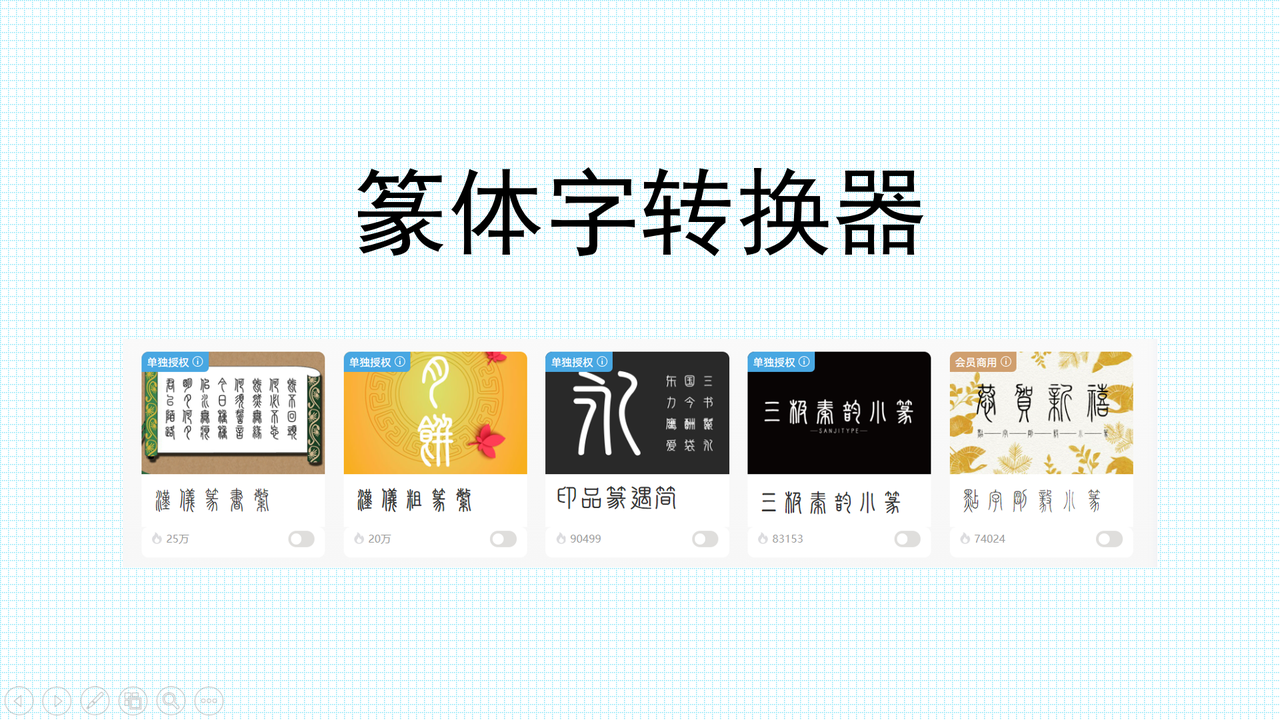
篆体字转换器哪个好?用字由就够了!
书法字体一直都是设计行业的潮流,因为它不仅保留了古代书法的文化底蕴,还能给作品增添一份庄重感和专业感。但传统的篆体字生成器问题太多了,比如打开之后经常弹出广告、生成的字体效果很差又不规范、有时候判断不了版权归属。今天就给大家介绍一款完全稳定的篆体字转换器——字由,它是国内领先的字体管理工具,拥有海量正版的字体资源,推出了多款高品质篆书字体,更是与汉仪字库、三级字库等头部字体厂商深度合作,字体版权完全可以得到有力保障。本文将从字由的优势、篆体字转换流程到热门篆体资源推荐三个方面详细来介绍,一起来看看吧!
一、为什么选字由?篆体字转换器的核心优势
大家都知道,市面上的篆体字转换器五花八门,随便一搜就能搜出一大堆,为什么要给家推荐字由?原因非常简单——字由可以解决设计师真正的痛点,不仅仅是实现篆体字转换这种单一的需求。它是面向设计师用户提供字体应用,管理,授权服务,并提供 AI 识字、字体特效等实用设计工具的全方位字体管理神器。
3.AI 字体功能一键生成篆书效果
字由除了优质的字体资源,还内置了 AI 字体功能,里面藏有大量艺术字模板。用户只需要选择自己心仪的模板,输入文字内容,就可以一键获得同款字体,下载为透明背景的 PNG 图片之后,直接拖进海报作品中就能用。
二、篆体字转换流程
1.输入文字一键转换当前效果
第一步:进入字由的字体资源页面
在搜索引擎搜索“字由”,选择官网进入,在首页顶部导航栏点击“全部字体”。
第二步:按风格筛选篆体字
用户可以直接在搜索框输入“篆”,下方页面就会弹出字由内的篆体字模板,点击选择一款自己想要的风格。
第三步:输入文字完成转换
在字体详情页面,在文本框内输出文字,就能转换为当前篆书字体的效果。
2.客户端实现在 PS、sketch 中的字体一键转换
第二步:搜索篆书字体。
用户注册登录字由客户端之后,在客户端的搜索框输入“篆书”,或者通过左侧筛选栏进行筛选,即可看到字由整理的专业篆书资源。
第三步:一键激活并完成字体转换
在 PS 等设计软件中选中需换字文本,回到字由客户端,找到心仪的篆书字体,点击右侧“激活”按钮,即可完成字体应用。后续你想怎么修改字体都可以在设计软件中进行了,这款字体就归你了!
三、热门篆体字资源推荐
1.汉仪篆书繁(单独授权)
汉仪篆书繁是汉仪字库推出的经典篆书字体,笔致遒劲,间隔均衡,追求偏长秀气和幽雅、古朴,是字由平台上最受欢迎的篆体字体之一。线条没有丝毫现代的锐利感,非常圆润稳重,自带一种深厚的历史底蕴。这款字体适合用于古籍封面、电子排版、古风海报、传统节庆礼盒包装等场景。
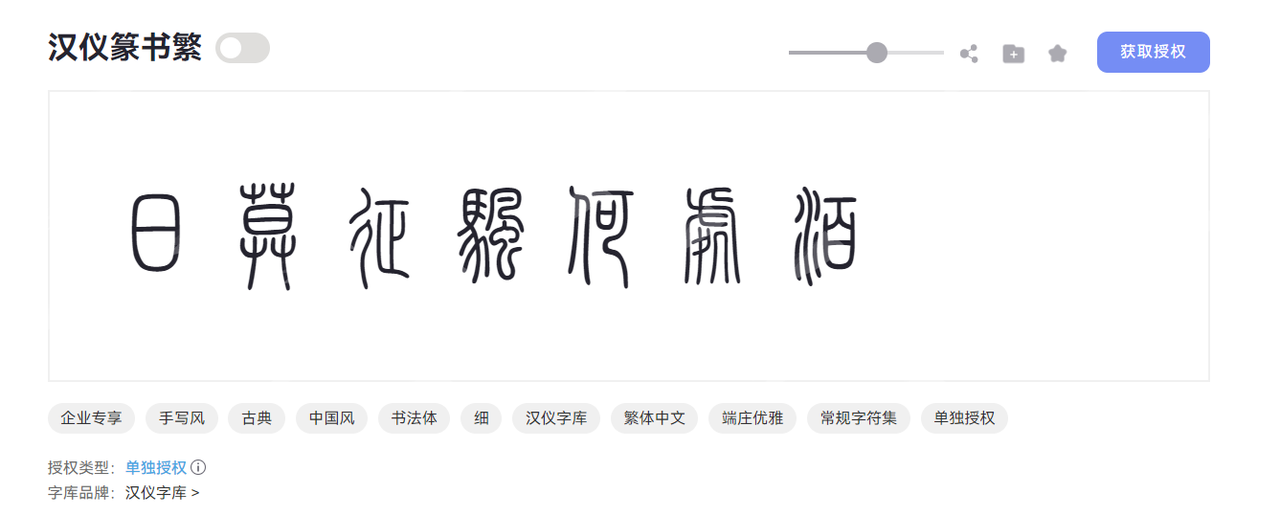
2. 三极秦韵小篆(单独授权)
三极秦韵小篆是三极字库出品的秦朝风格篆书字体,保留了秦朝时期篆书的特点,圆润均匀的线条、修长的字形、近似左右对称的结构。但是相比秦篆,它的笔画更有手写的温度感,线条变化比较贴近毛笔书写的真实质感,给人一种古典且温柔的美感。该字体适合用于文创设计、古风餐厅菜单、春联、文艺作品封面等文人气息较重的场景里。
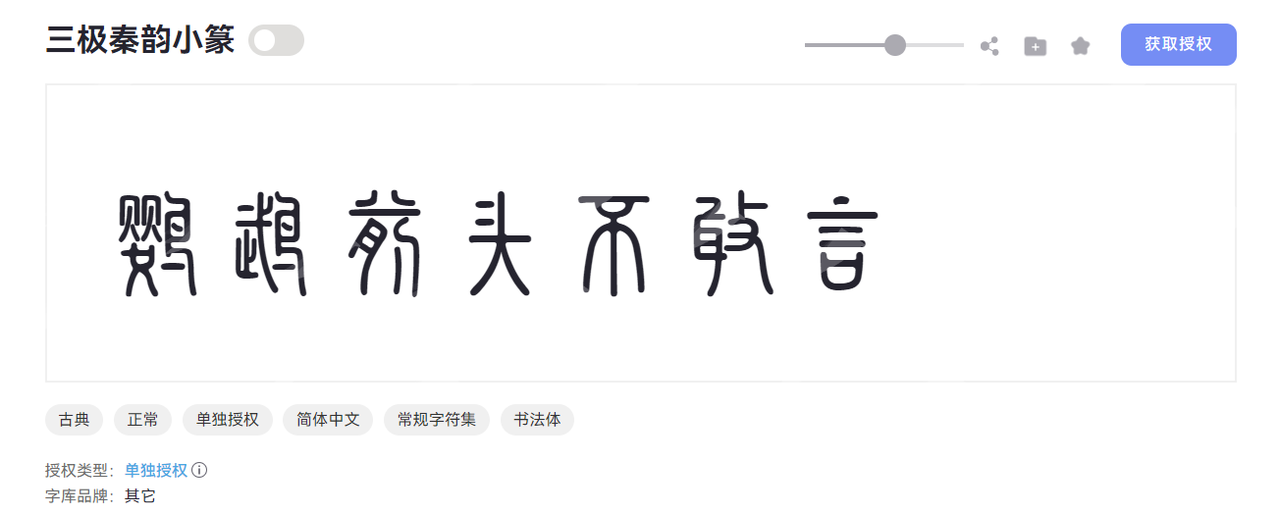
3.汉仪粗篆繁(单独授权)
汉仪粗篆是是由汉仪字库开发的一款现代艺术篆书字体,比汉仪原有的篆书笔画更粗一些,完美地融合了古典韵味与现代设计感。在古典小篆典雅匀称的结构基础上,进行了大胆的现代化、美术化处理,将笔画大幅加粗,形成强烈的块面感与视觉张力,同时保留了篆书特有的婉转流畅的笔意和装饰性。该字体适合用于国潮品牌 logo、武侠类书籍封面、游戏页面设计、音乐会海报等艺术气息浓烈的场景。
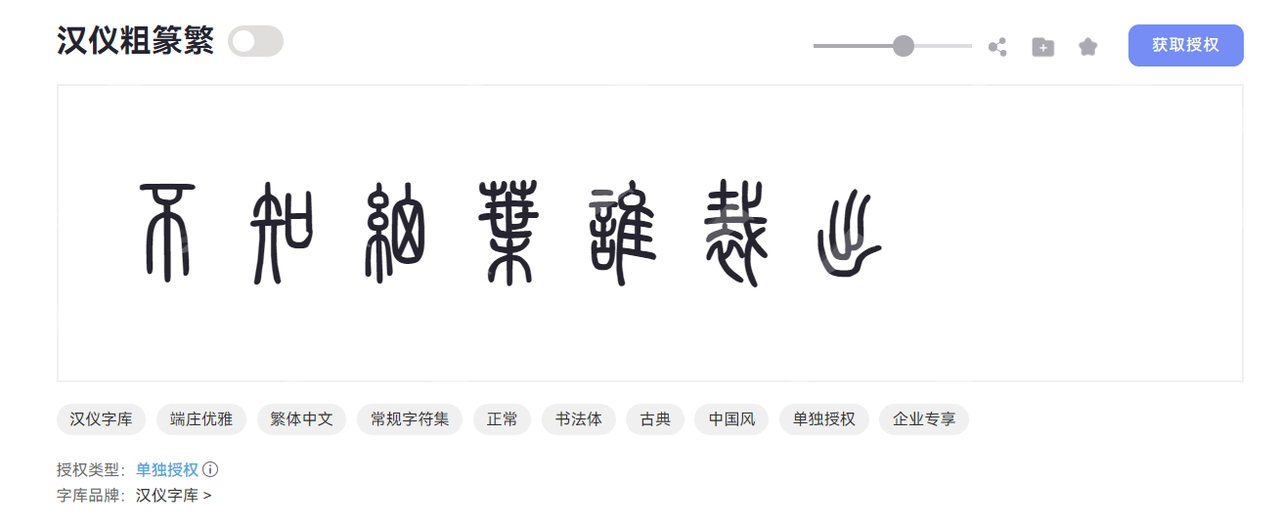
以上就是关于字由的详细介绍,用它来进行篆体字转换真的是再方便不过了!从多样化且实用的功能到全能的字体版权保障,再到丰富的篆体资源,更是优化了字体应用的流程,完全满足设计师在篆体设计中的所有需求。不管是古风文创、影视创作还是做国潮设计、品牌 logo 等,字由官网帮你轻松生成古朴庄重的篆体字效果,再也不用找那些不靠谱还一堆广告的篆体字转换器了!赶紧收藏好这份指南,下次直接打开字由官网,找到最合适的篆体字轻松提升作品质感!